墓碑的标准具有对基础內容的规定,即不一样的墓碑有不一样的健身培训规定,又有对字体样式的规定。
从古到今,最常见的碑文字体有四种,分别是:魏碑、行楷、手书、隶书墓碑。这四种字体样式分别都是有不一样的特性,也分别拥有 自身的表达效果。总得来说,字体样式的挑选对不仅是以便清理墓牌,更寄托了一种对先祖的尊重和想念之情。
结束语:好的事情总给人一种好的享有。这些可以广为流传出来并被后代赞许的墓碑通常具有精彩纷呈的內容,也拥有 让人啧啧赞叹的中国书法,即其字体样式。
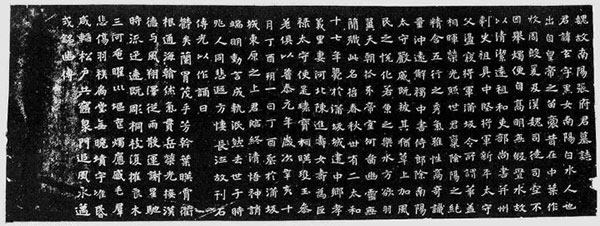
魏碑是北魏至今产生的碑刻毛笔书法字体,它的特性是豪爽、刚劲有力,笔锋独特。极知名的如《郑文公碑》、《张猛龙碑》、《高贞碑》、《元怀墓志》及《张玄墓志》。
行楷笔迹顺畅,洒脱,具有正楷的端稳华康,又有行书的顺畅,是一种很火爆的字体样式。如唐代的《定武兰亭》:
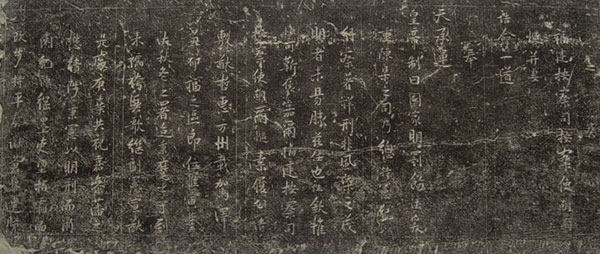
手书碑文字体因人有所不同的,字体样式方式多元化,与其说是它的表现力,还比不上注重其留念实际意义。如明张瑞图手书著作:
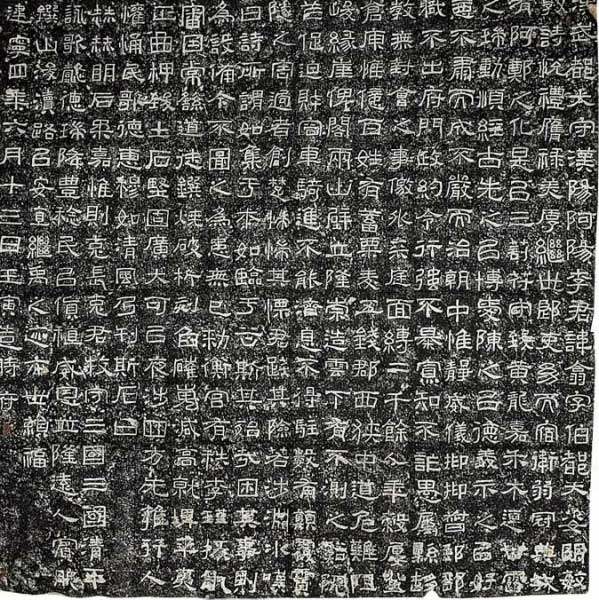
隶书在全部的字体样式中是最端庄的,而且整齐粗狂,适用宽敞厚实的碑体。如《汉西峡颂》拓片: